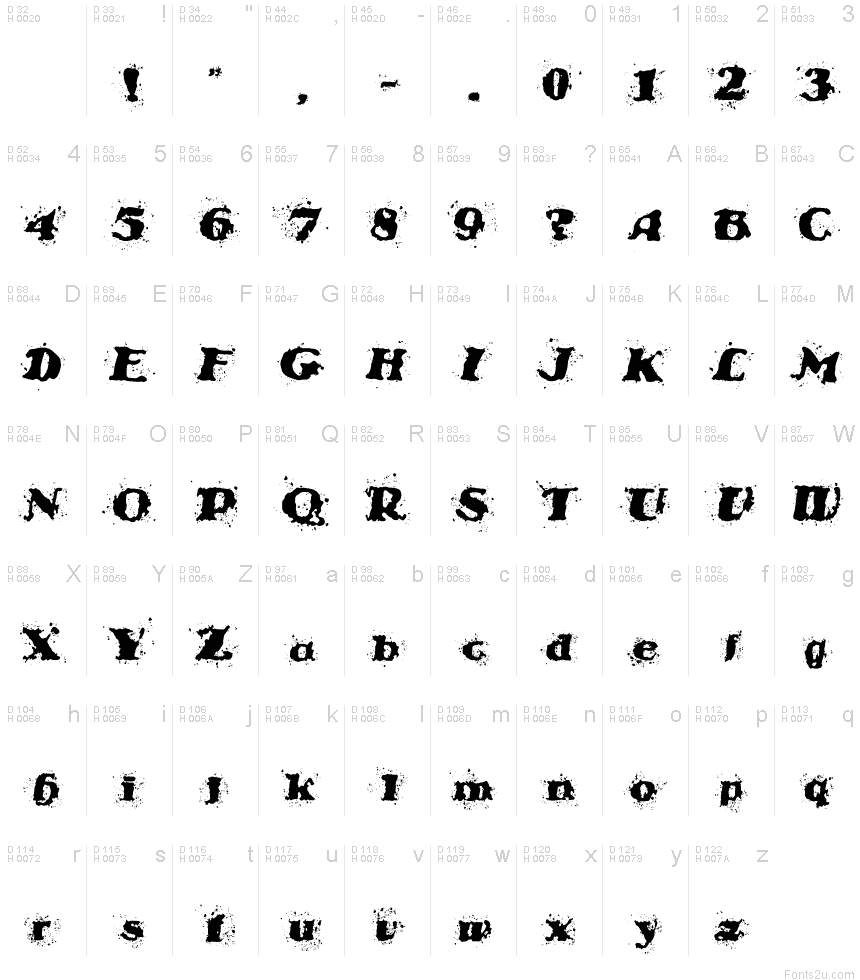
Stable No od Veredgf to darmowy, ozdobny krój pisma typu display, inspirowany zachlapanym tuszem i estetyką vintage. Jego szorstki, poplamiony charakter sprawia wrażenie czegoś odbitego stemplami, przeciągniętego i lekko niestabilnego. Litery wydają się jednocześnie ciężkie i miękkie w krawędziach, z poszarpanymi konturami i rozpryskami, które zmieniają każde słowo w namacalny, niechlujny ślad, a nie sterylny nagłówek.
Dzięki temu ten darmowy font to naturalny wybór na plakaty koncertowe, okładki zinów, tytuły horrorów, surowe opakowania czy buntownicze projekty marek, w których rozrzut i smugi same budują klimat. Sprawdzi się także w krótkich wstępach redakcyjnych i wyrazistych grafikach do mediów społecznościowych, zwłaszcza gdy zależy Ci na efekcie zwietrzenia i odrobinie chaosu.